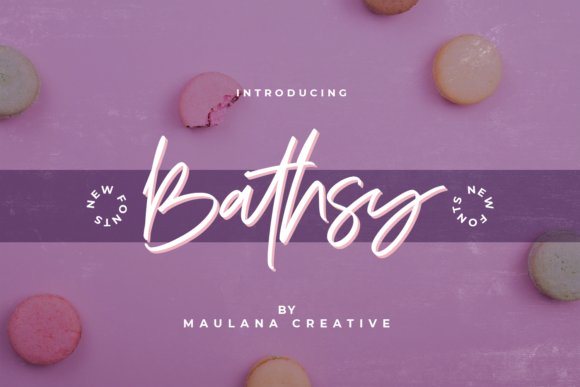
Creativefabrica Bathsy Font
[Creativefabrica] Bathsy Font
Батси - милый и дружелюбный рукописный шрифт.
Его естественный и неповторимый стиль делает его невероятно подходящим для большого бассейна дизайна.
Единственный предел - ваше воображение!